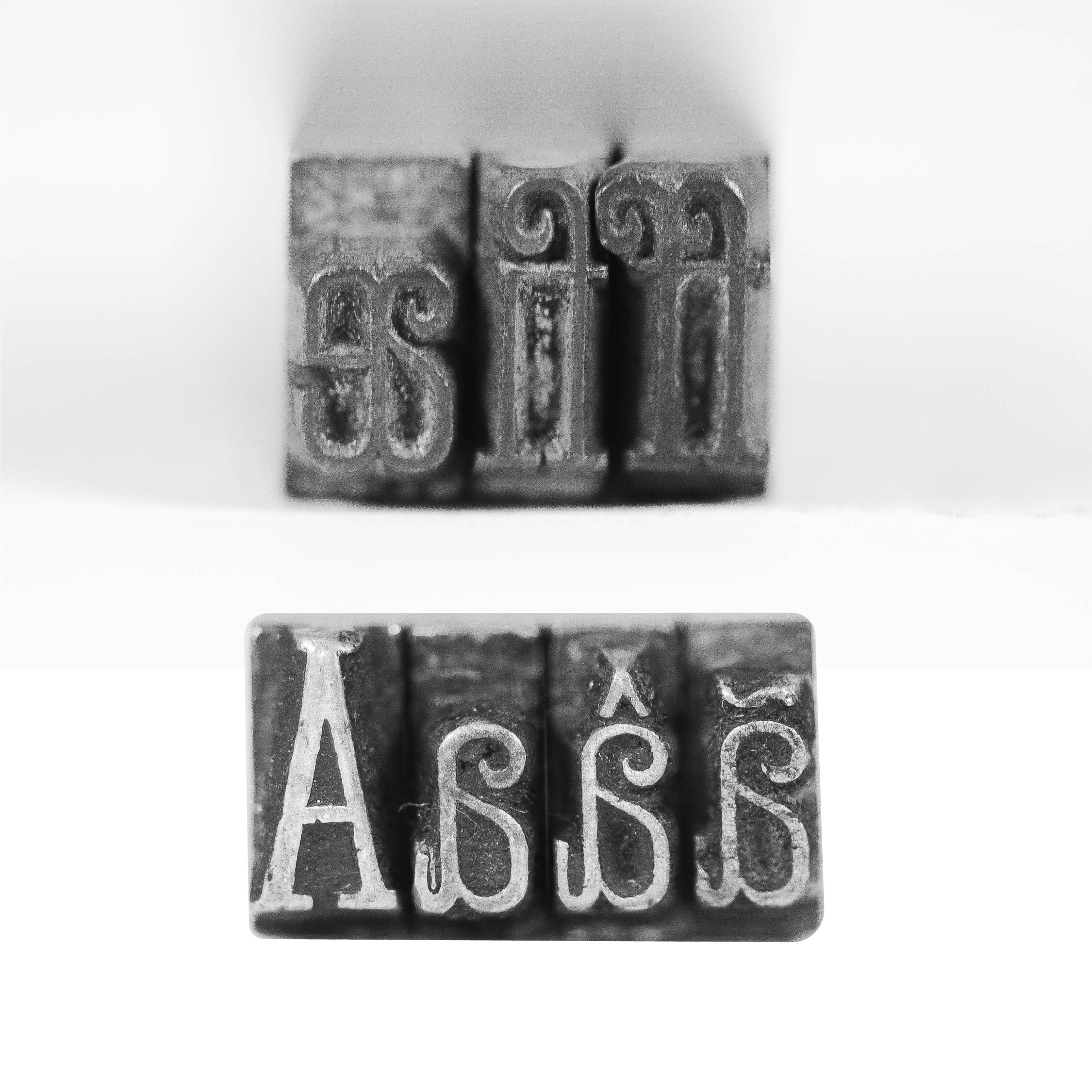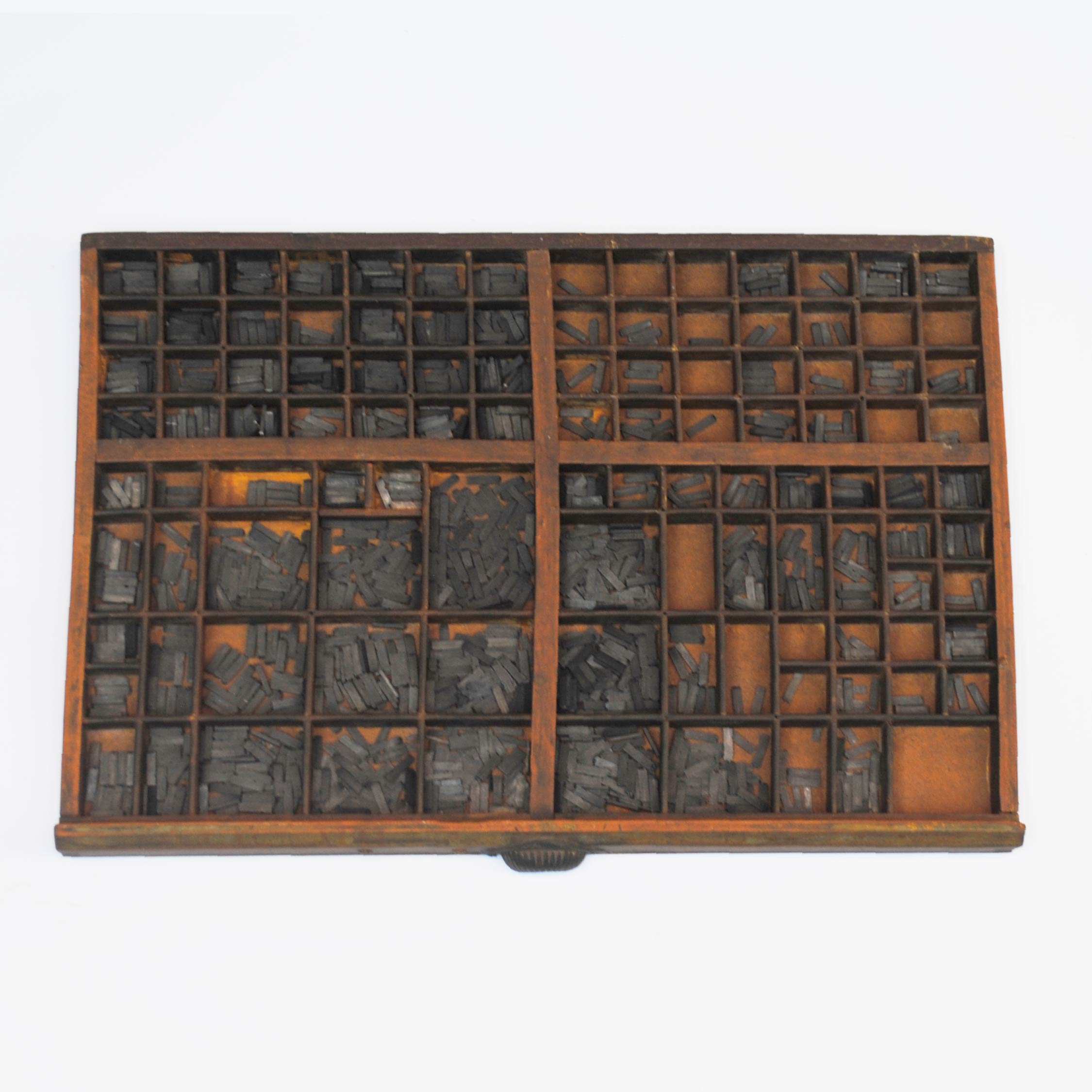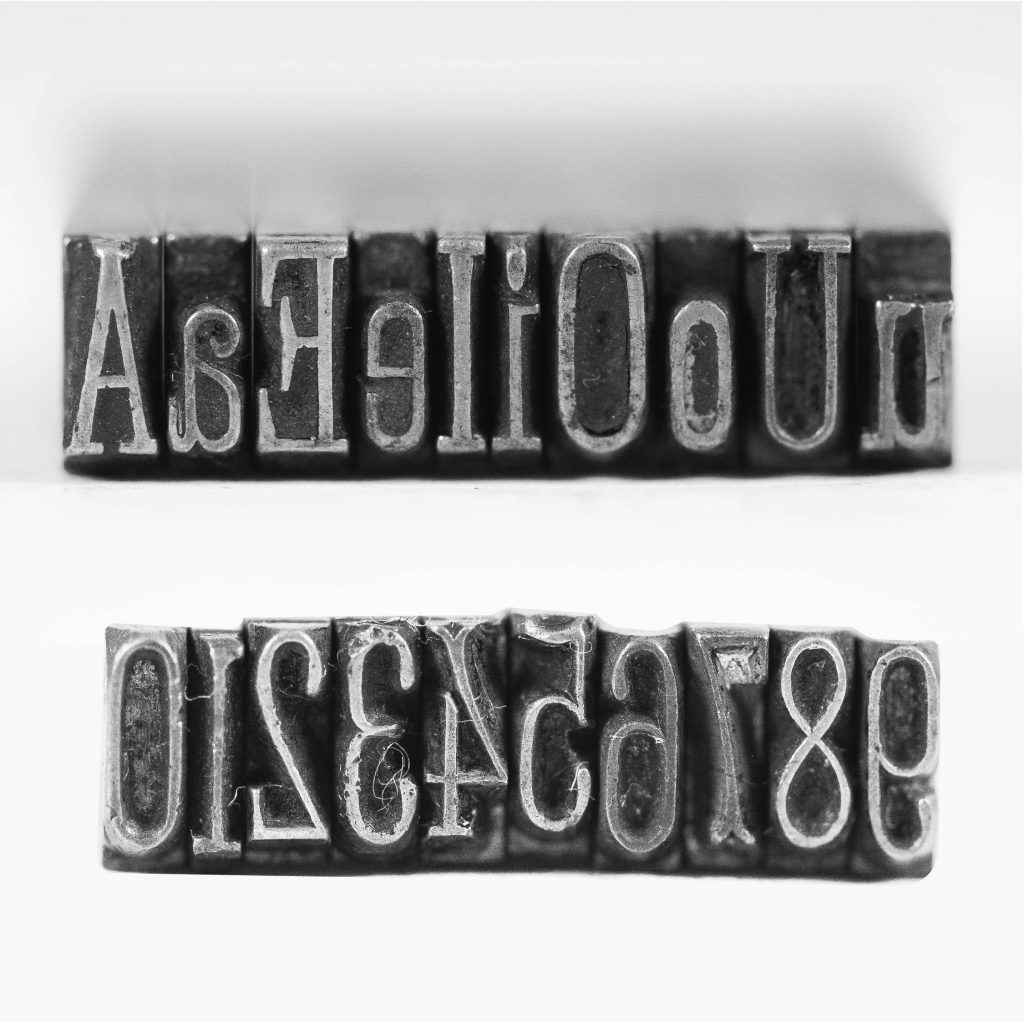
Faltam acentuadas de algumas letras, como Íí, Ìì,Îî.
Fonte muito semelhante à família Rinascimento Affilate (Nebiolo, [ca. 1900]). Por se tratar de um nome genérico, não foram encontradas referências que pudessem indicar detalhes a respeito de sua origem e autoria, dificultando saber mais sobre seu desenho original. Após a comparação digital, foi confirmada essa semelhança com a Rinascimento Affilate em todos os aspectos analisados.